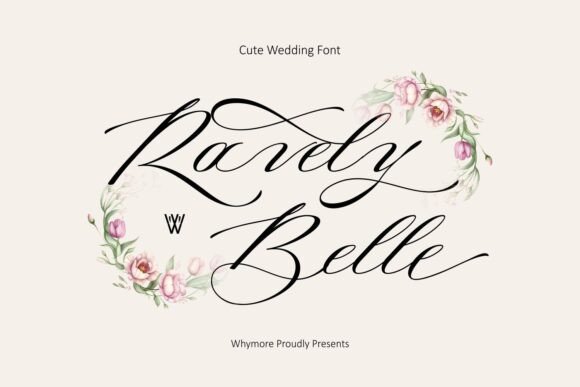
Ravely Belle
適切なデザイン要素を見つけるのは難しい場合がありますが、Ravely Belleは作品を即座に引き立てる優れたコレクションを提供します。
POD(オンデマンド印刷)製品、結婚式の招待状、またはソーシャルメディアのグラフィックを作成している場合でも、Ravely Belleは理想的です。